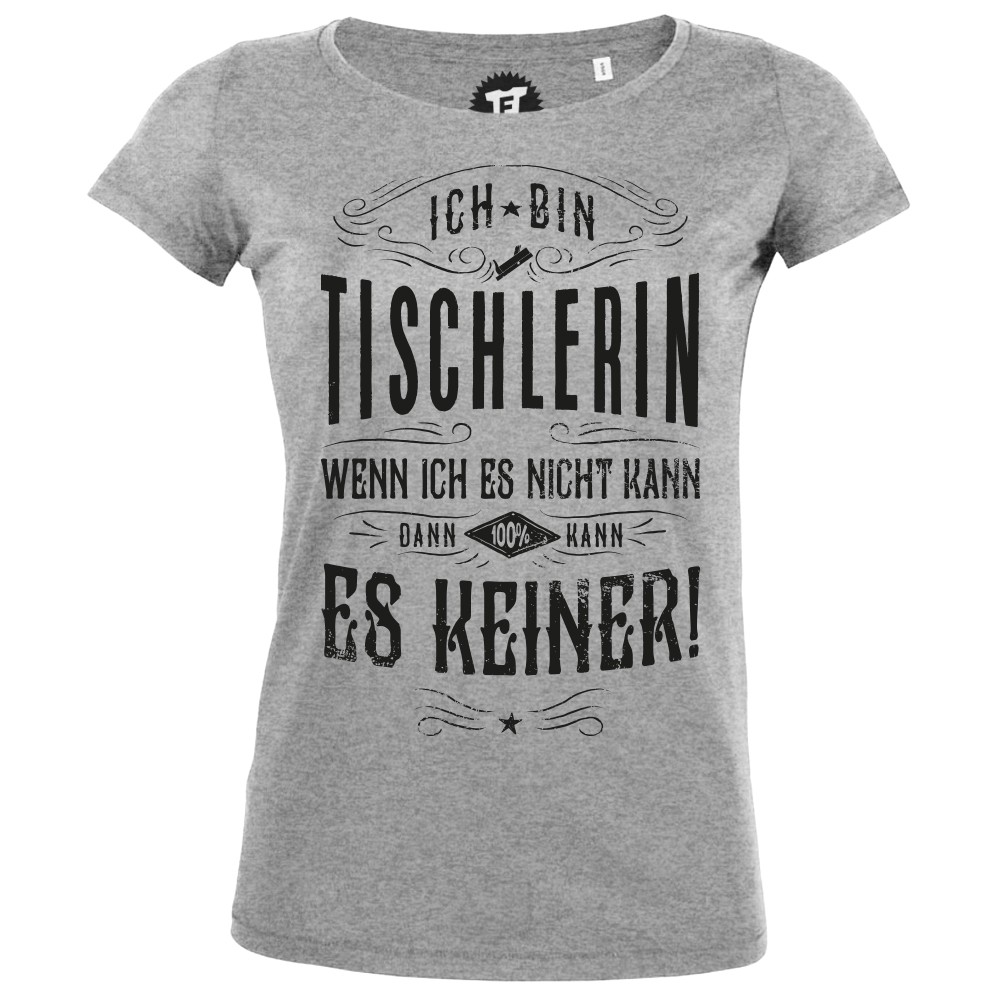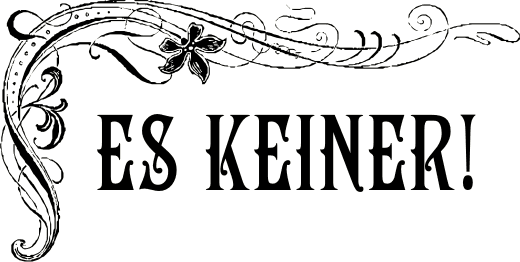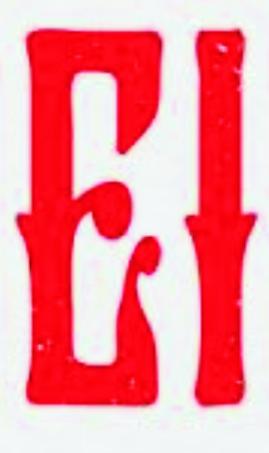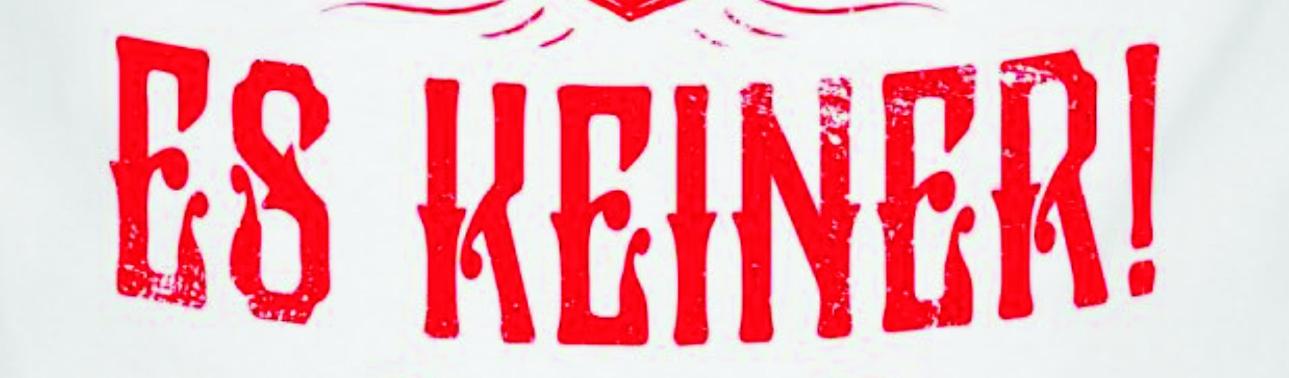
Verzweifelte Suche nach dieser Schrift
die üblichen fragen: woher hast du das? was ist es? gibt’s mehr davon? brauchst du genau diese schrift oder reicht etwas ähnliches?
also ein kollege vom rettungsdienst möchte von mir ein shirt gemacht haben, und die vorlage hat genau diese schrift, die er mir mitgebracht hat....
und ich finde diese schrift einfach nicht dann bin ich auf dieses forum gestossen... und erhoffe eine lösung...
es könnte auch eine ähnliche schrift sein.....
es gibt einen freefont namens »famoose«. der kommt in die nähe. wenn du generell nach jugendstil-fonts suchst, wirst du mehrere in der anmutung ähnliche finden.
Nicht weinen. Es sollte klappen, wenn Du in das Suchfenster »font famoose« eingibst und danach bestätigst, dass nur nach »font famoose« und nicht nach »font famous« gesucht werden soll.
mehr hab ich leider nicht …
Ich schon: